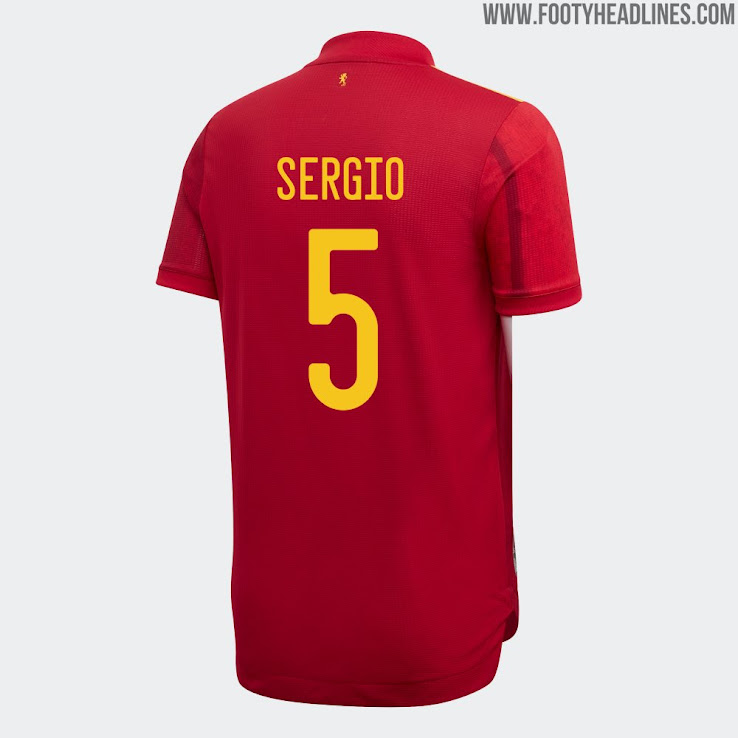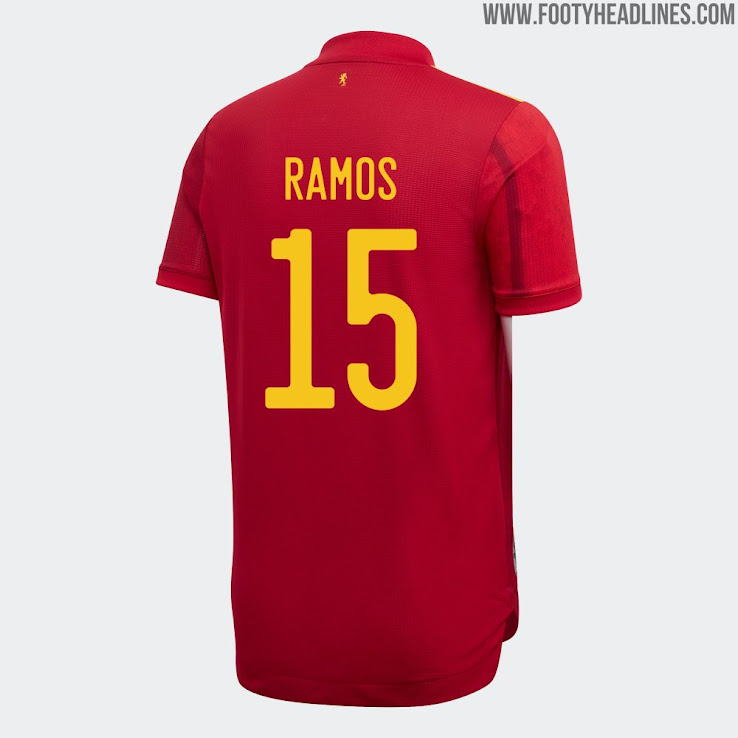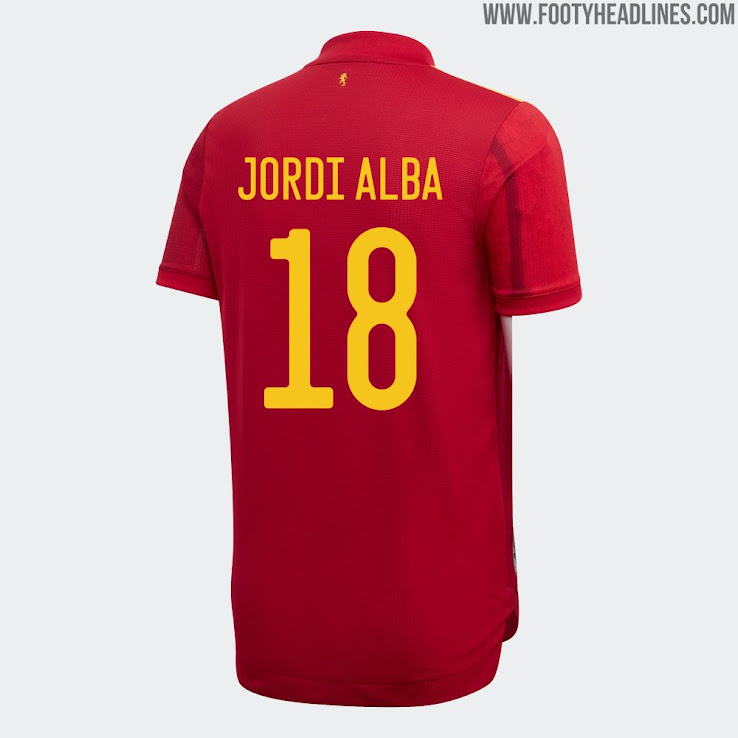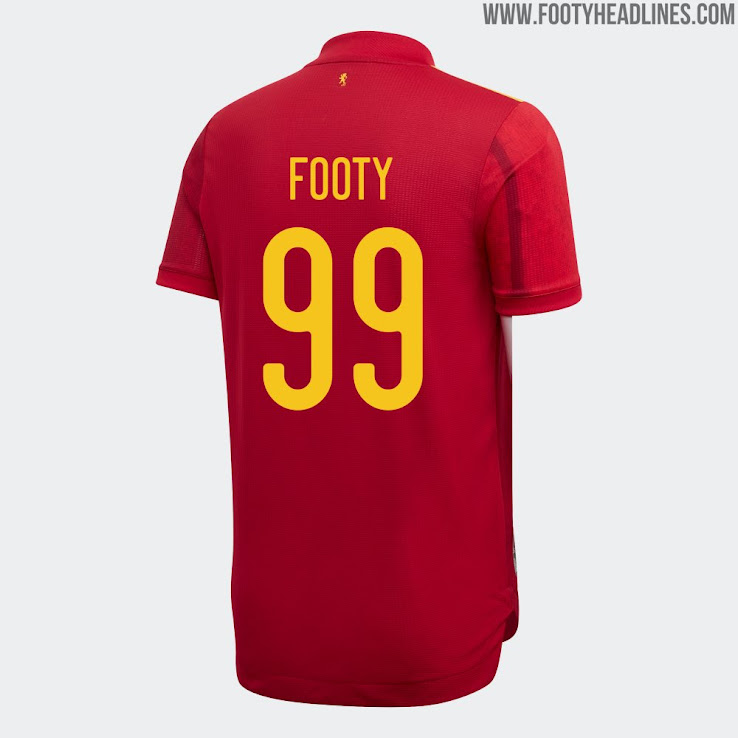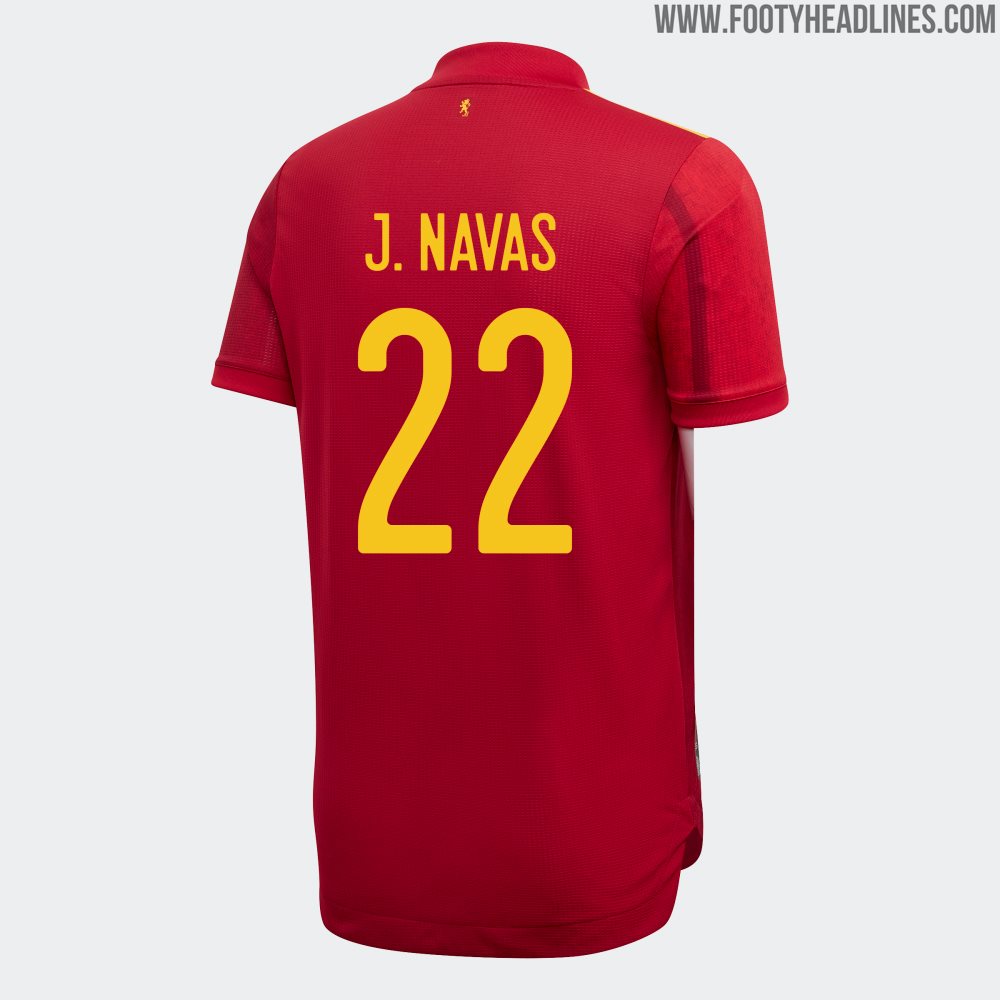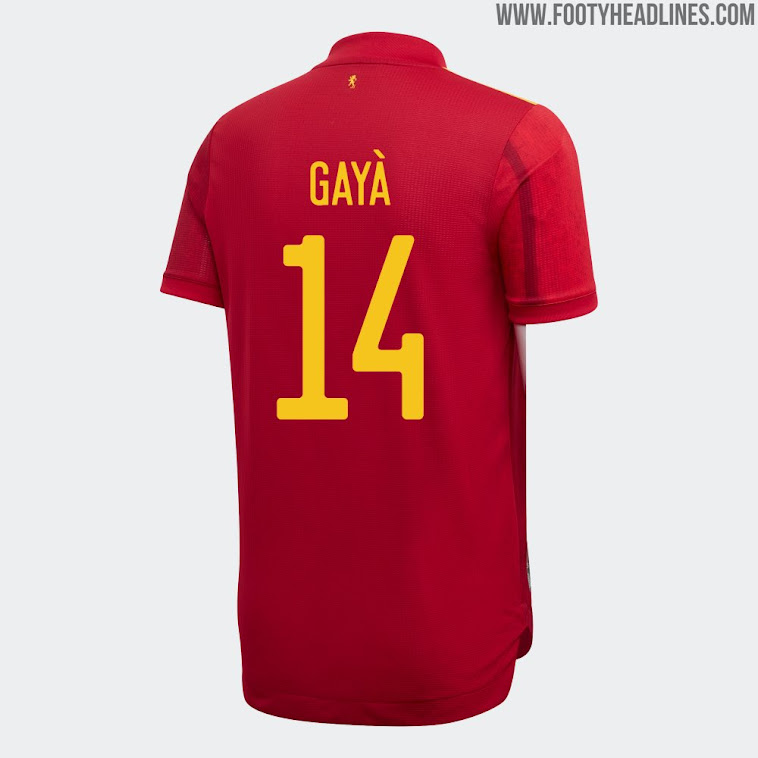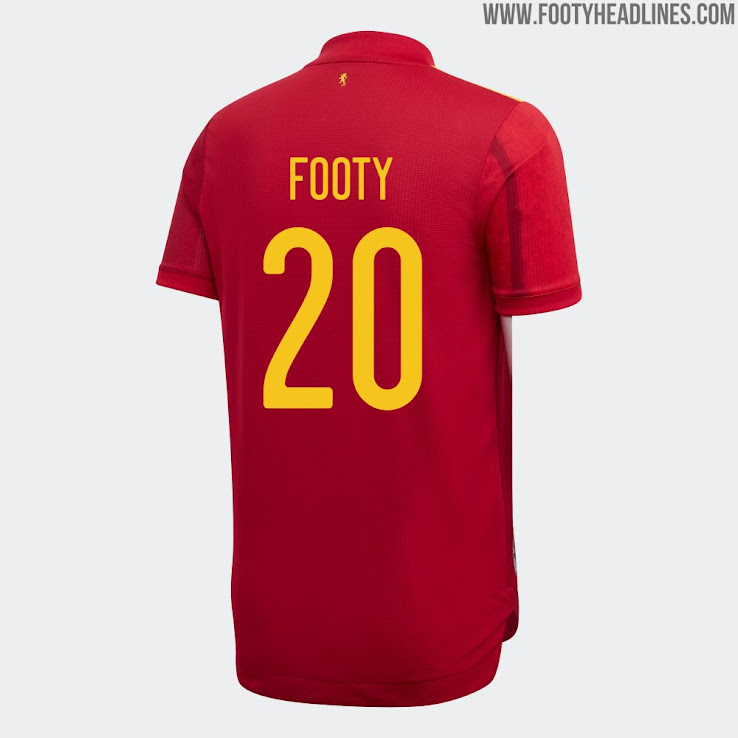
Spanien EM 2020 Schriftart Veröffentlicht
Während Deutschland für sein EM 2020 Trikot eine einzigartige Schriftart erhielt, teilen alle anderen Adidas-Nationalmannschaften die Schrift, inklusive Spanien. Hier ist ein genauerer Blick auf die Spanien EM 2020 Schriftart.
Adidas Spanien UEFA EM 2020 Schriftart
Die Schriftart des Spanien EM 2020 Trikots ist die gleiche wie Japans, abgesehen von der Grenze und dem subtilen Wolkenmuster auf der letzteren.
Interessanterweise verzichtet die Spanien UEFA EM 2020 Schriftart auf Adidas Produktbildern auf weitere Details. Wir gehen jedoch davon aus, dass zumindest das Verbandswappen, ähnlich wie bei der Schriftart von Japan und Deutschland, am Ende der Nummern in den Spielen stehen wird.
Die neue Schriftart wird von Spanien in allen Spielen ab heute verwendet werden, einschließlich der EM 2020.
Wir gehen davon aus, dass die Schrift für das Auswärtstrikot verwendet wird.